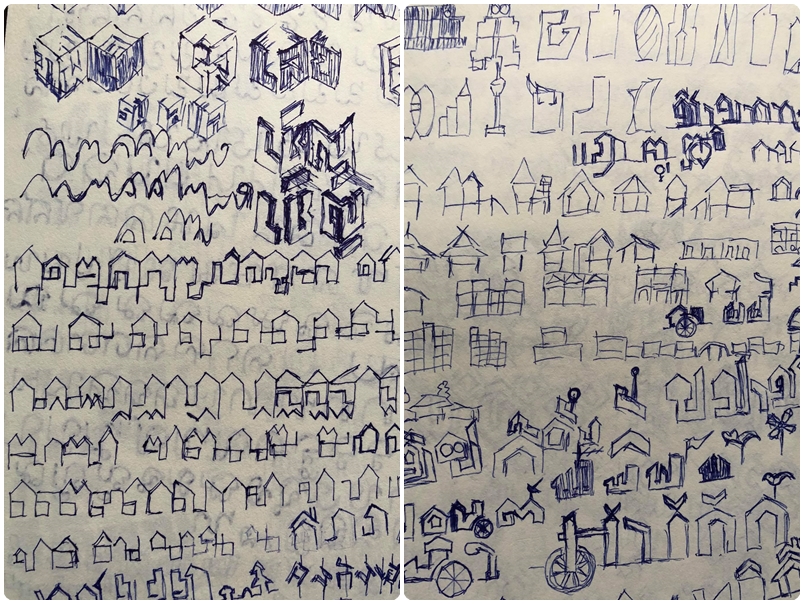
ฟอนต์ บ้านๆ
ว้ายภาพประกอบน่ารัก คาเฟ่อะไรเนี่ย :25:
ภาพฟ้อนต์นี้ไปวางอยู่บนนิตยสารท่องเที่ยวลอยมาเลยครับ  :12: :12:
ว้ายภาพประกอบน่ารัก คาเฟ่อะไรเนี่ย :25:
เบื้องหลัง
ฟอนต์บ้าน เกิดจากขั้นตอนการทำ ฟอนต์เสียง
เบื้องหลังอย่างโหด :12:
ชื่อฟอนต์ : บ้านๆ
ฟอนต์บ้านๆ จ๊ะ
ระบบ mark ช่วยให้ ฟอนต์บ้าน มีอิสระในการออกแบบ สามารถสร้างสระบน วรรณยุกต์ ให้กลายเป็นเครื่องหลังคา ของบ้าน(พยัญชนะ)แบบต่างๆ ทั้งรูปแบบและความสูง
เนี่ยน่ารักม้าก :25:
มีการเติมท็อปปิ้ง